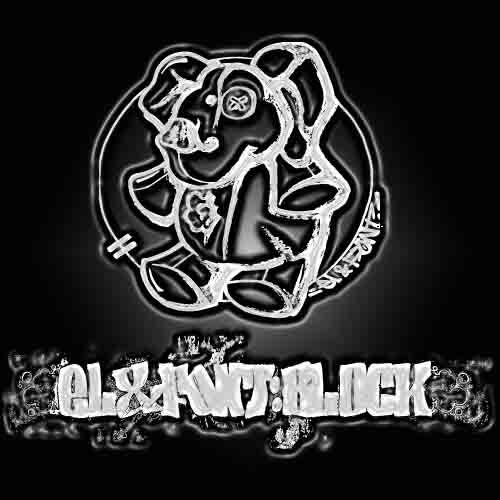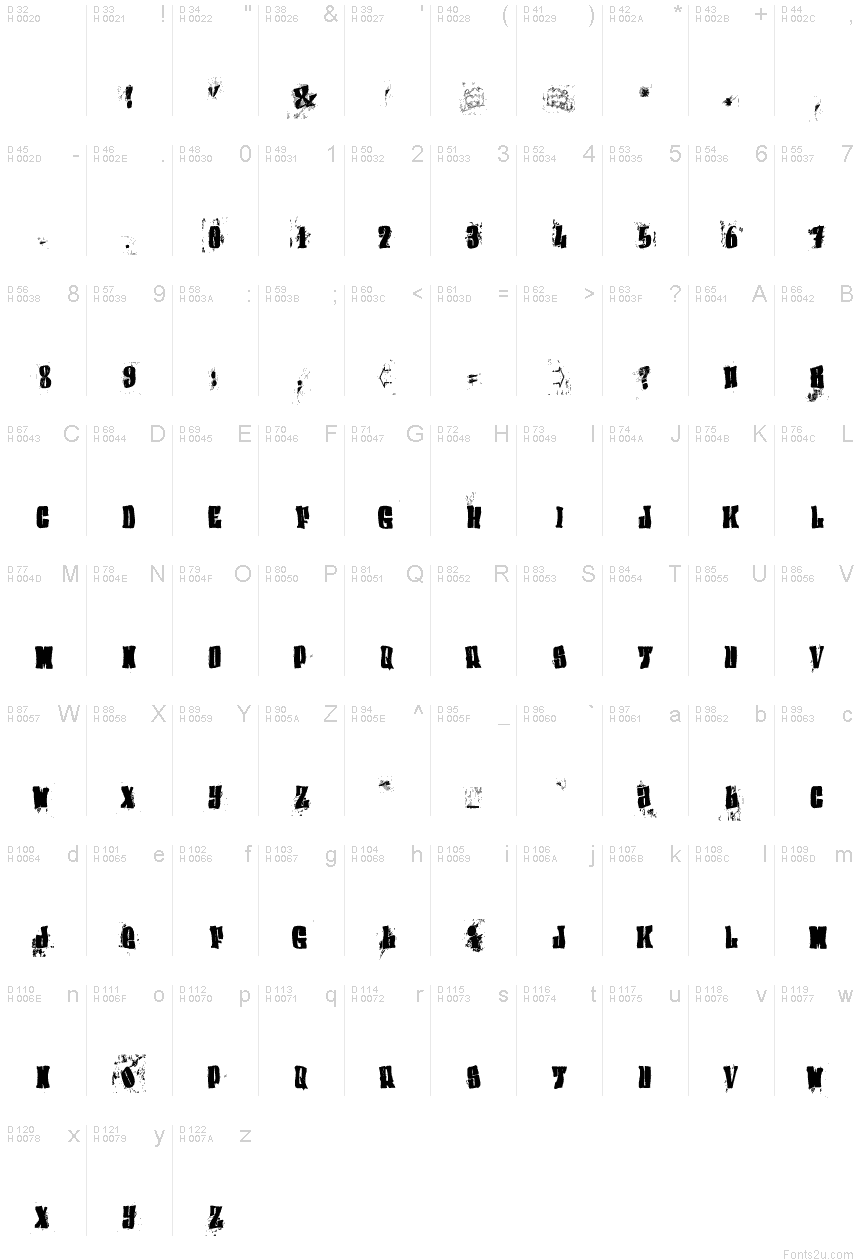
El&font Block od Typeface to darmowy, zniekształcony font typu display, który wygląda, jakby został przeciągnięty przez mokry tusz i rzucony na surowy beton. Masywne, „spuchnięte” litery zlewają się w plamy i zadrapania, nadając każdemu słowu surową, punkową energię DIY niczym z kserowanego zinau. Nierówne kontury i ciężkie, czarne kształty tworzą głośny, chaotyczny rytm, który natychmiast przyciąga wzrok.
Z El&font Block Twoje nagłówki nie szepczą – one krzyczą. Ten darmowy font świetnie sprawdzi się na okładkach albumów, plakatach horrorów, ulotkach imprez undergroundowych, grafikach streetwearowych, w brandingu sportów ekstremalnych czy odważnych kampaniach społecznościowych. Użyj go w dużym rozmiarze dla maksymalnego efektu, a w tekście głównym połącz z wąskim, czystym krojem bezszeryfowym, aby wyostrzyć kontrast i pozwolić teksturze grunge naprawdę wybrzmieć.
(el&font BLOCK) — Prezentacja czcionki